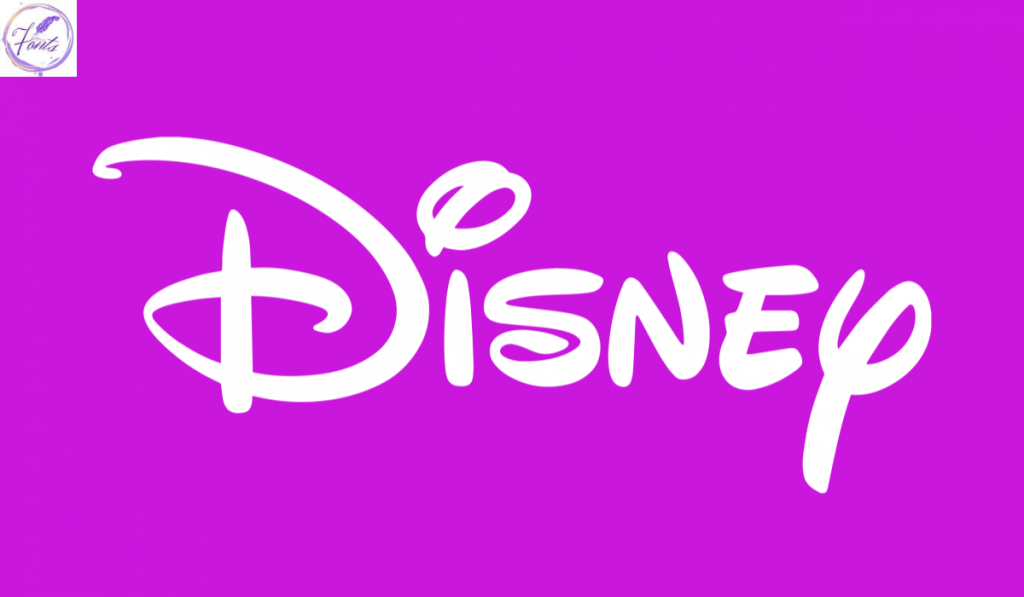
Font chữ Disney việt hóa
Bộ Font: Disney
Phân loại: Cá tính, Độc đáo, Vui vẻ, Hoài niệm
Kiểu chữ: Kiểu chữ viết tay (script)
Độ dày: Thin, Light, Regular, Bold, Black
Font chữ Disney là biểu tượng của sự thân thiện và phấn khích, đã trở thành một phần không thể thiếu trong các tác phẩm liên quan đến thế giới diệu kỳ của Disney. Với nét chữ đầy màu sắc và vui nhộn, font này thường xuyên được sử dụng trong các sản phẩm cho trẻ em, truyện tranh, và quảng cáo. Việc việt hóa font chữ Disney giúp người dùng Việt Nam dễ dàng áp dụng vào các dự án sáng tạo, mang đến cảm giác quen thuộc nhưng cũng không kém phần mới mẻ.
Đánh giá font chữ Disney
Font chữ Disney được cộng đồng thiết kế đánh giá cao bởi tính ứng dụng và sức hút đặc biệt của nó. Font này không chỉ góp phần làm sống động các tài liệu và sản phẩm truyền thông mà còn tạo cảm hứng cho những người sáng tạo nội dung dành cho trẻ em và gia đình. Sự việt hóa đã làm tăng thêm giá trị sử dụng của font chữ Disney tại Việt Nam, giúp nó trở nên gần gũi hơn với người dùng trong nước.